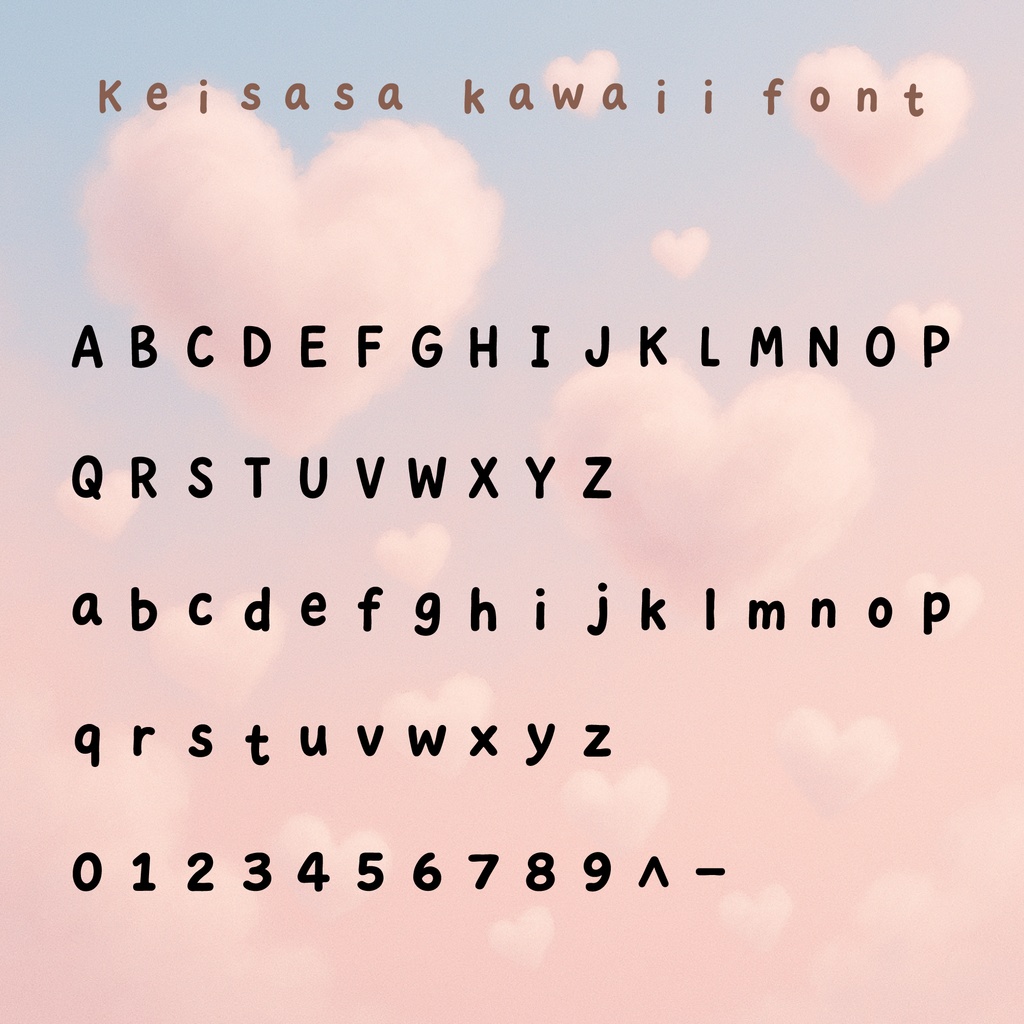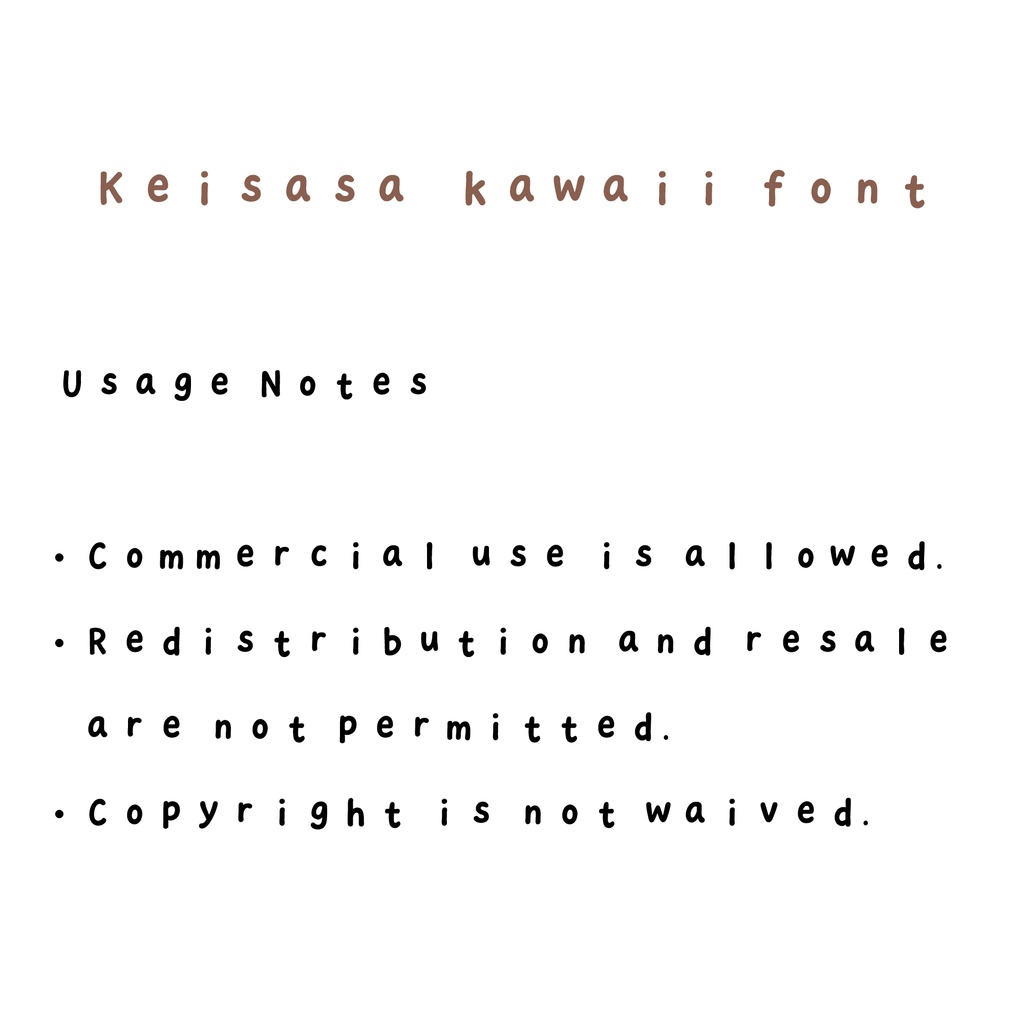
【商用可】Keisasa kawaii font|ゆるふわ・キュート系丸ゴシックフォント
ふんわり可愛い雰囲気の手書き風丸ゴシックフォント「Keisasa kawaii font」です。 やさしい曲線と丸みのある形状が特徴で、ポップで親しみやすいデザインに仕上げました。 見出しやロゴ、SNS画像、商品パッケージ、チラシなど、幅広いデザインシーンに活躍します。 特徴 商用利用可能(利用規約をご確認ください) ひらがな・カタカナなし(英数字と記号対応) ゆるふわ・キュート系デザインに最適 UIやアプリの見出しにも映えるシンプル構造 利用例 可愛い系のショップロゴやバナー 動画サムネイルやSNS投稿画像 イベントフライヤーやポスター オリジナルグッズやパッケージデザイン English Keisasa kawaii font is a cute, rounded, handwritten-style sans serif font with a soft and friendly vibe. Perfect for headlines, logos, social media posts, and product packaging, this font brings warmth and charm to any design. Features Commercial use allowed (please check the license terms) English letters, numbers, and symbols Ideal for cute, pop, and friendly designs Simple structure that works well for UI and app titles Great for Cute shop logos and banners YouTube thumbnails and social media posts Event flyers and posters Original goods and package designs